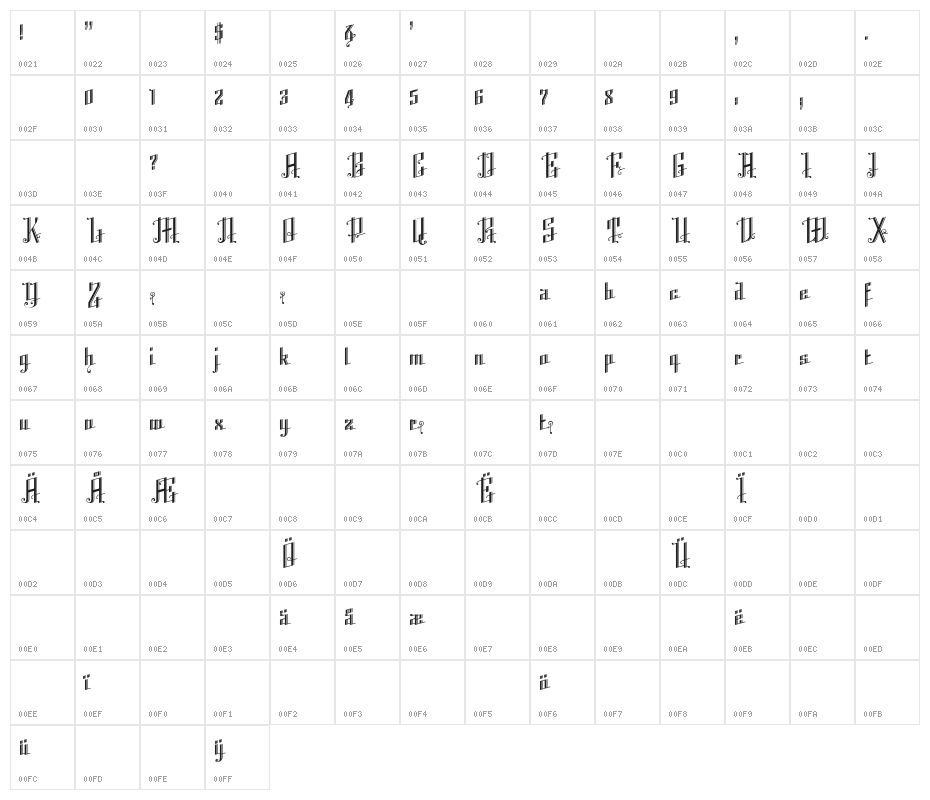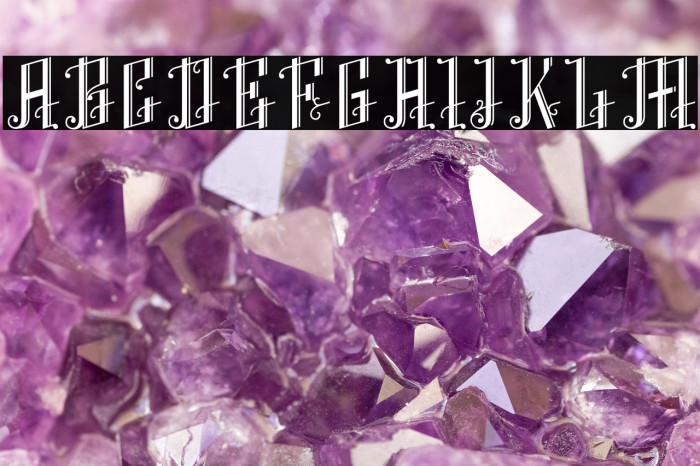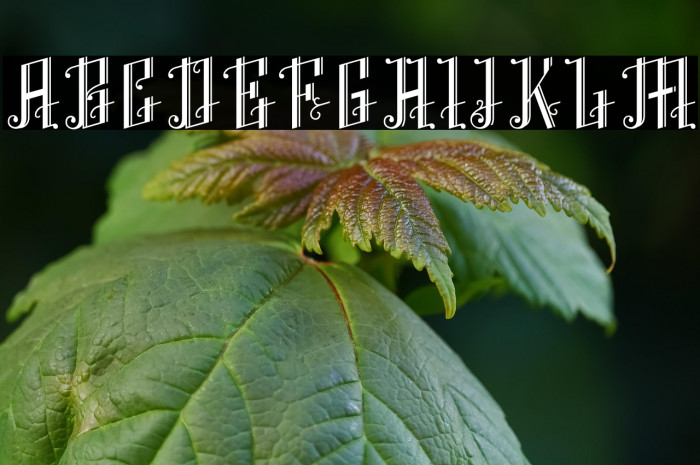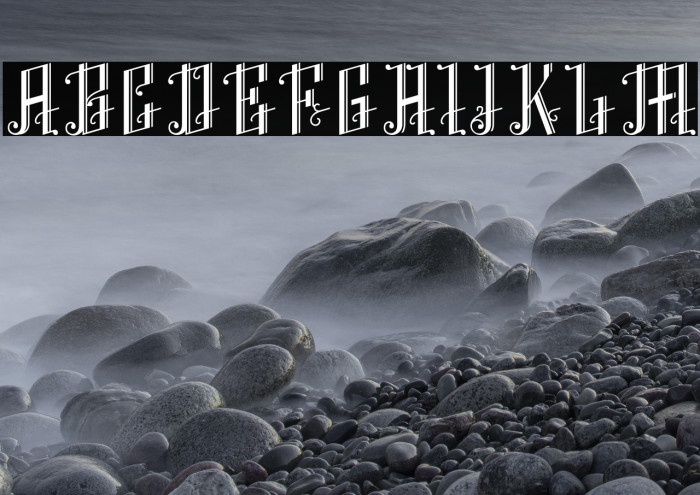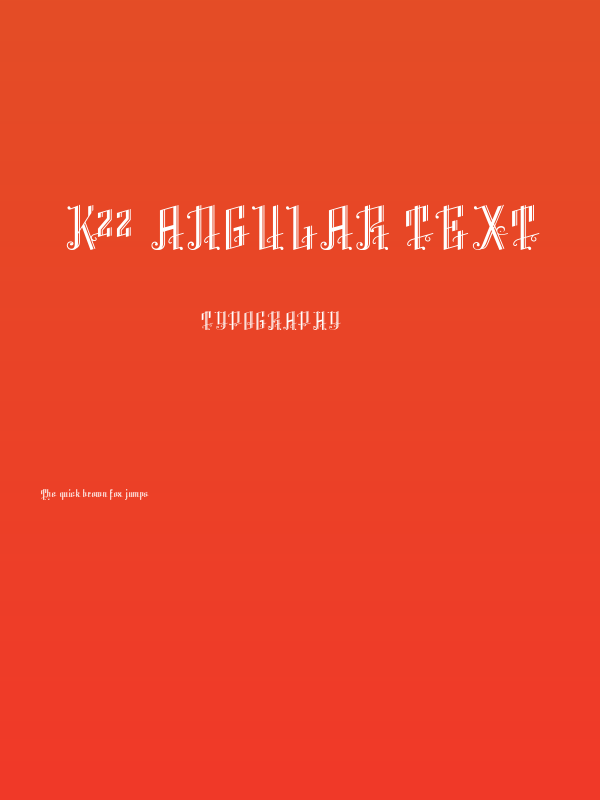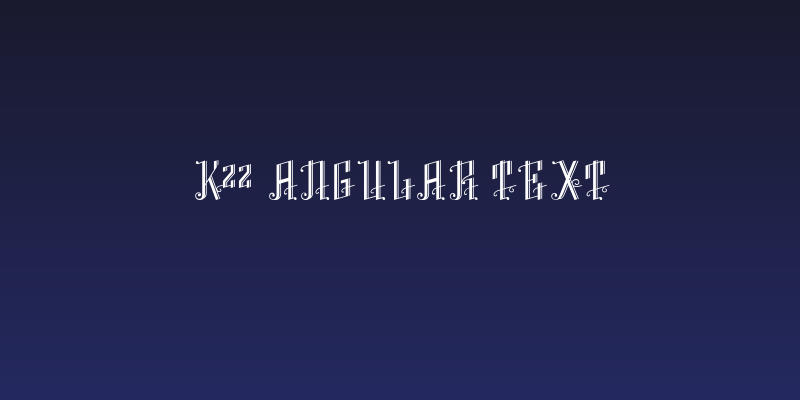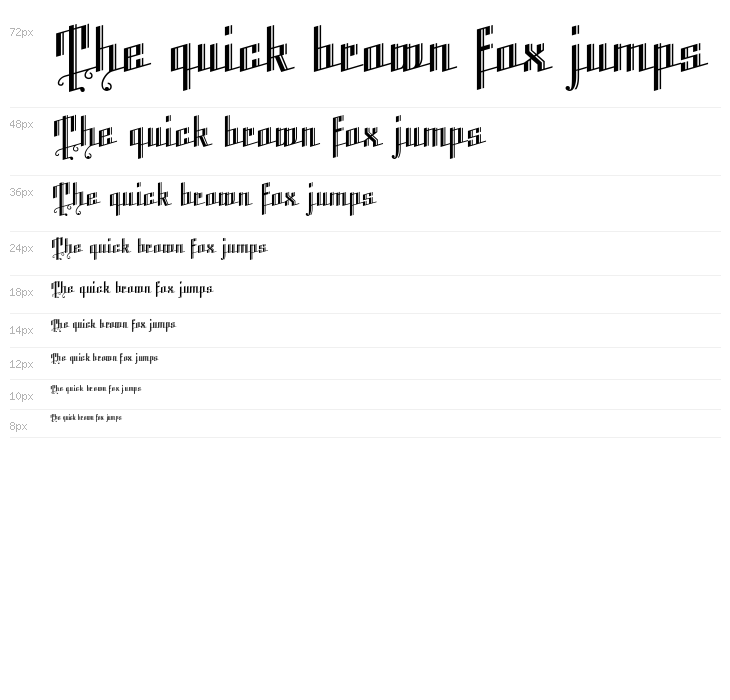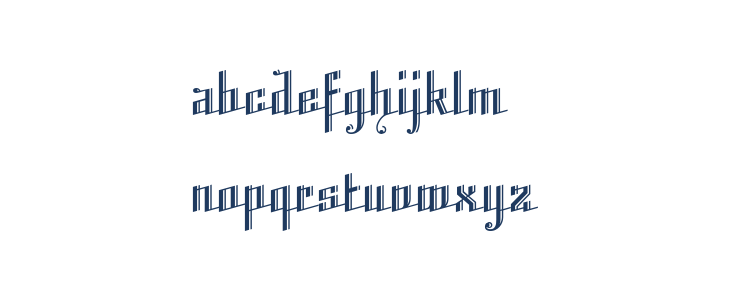
K22 Angular Text Font
✎ Gothic
| Progetti proposti | Ideal for projects requiring a dramatic and bold typeface, such as posters, album covers, or branding for edgy or alternative products. |